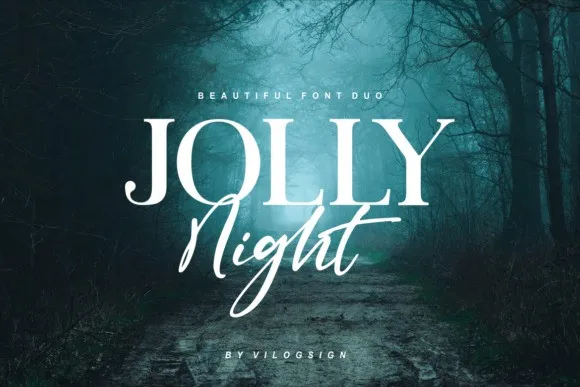
Jolly Night Font Duo – Download Grátis
Introduzimos Jolly Night Script & Serif, uma combinação única de script e serif que não deixará você indiferente. Esta elegante dupla de fontes vem com belas ligaturas e alternativas para trazer um toque criativo e aparentemente irreal a seus projetos futuros. Os designers da zziplex criaram este duo de fontes pensando em perfilar suas criações, oferecendo uma combinação perfeita entre a delicadeza de um script romântico e o encanto de uma serif elegante. A Jolly Night Script é suave e encantadora, enquanto a Jolly Night Serif é sofisticada e refinada. Jolly Night Script & Serif tem sido projetado para aumentar significativamente o nível de sua próxima criação visual. Se combinadas, estas duas belas fontes podem levar qualquer projeto design a um novo patamar, adicionando um toque único e fascinante à sua obra.